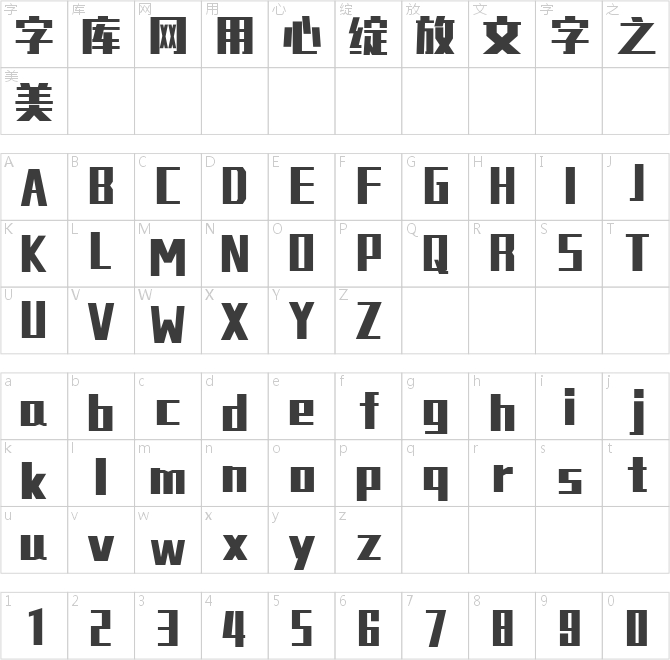
銳字工房金剛大黑簡1.0 詳情頁
字體名稱: 銳字工房金剛大
銳字工房金剛大黑簡1.0
銳字工房金剛大黑簡1.0字體字庫是一款讓人賞心悅目、百看不厭的中文字體,適合各類廣告和產(chǎn)品包裝設(shè)計應用,字體大小3.05MB,格式為ttf字體,上傳用戶是1733150348,作者/版權(quán)方為銳字潮牌